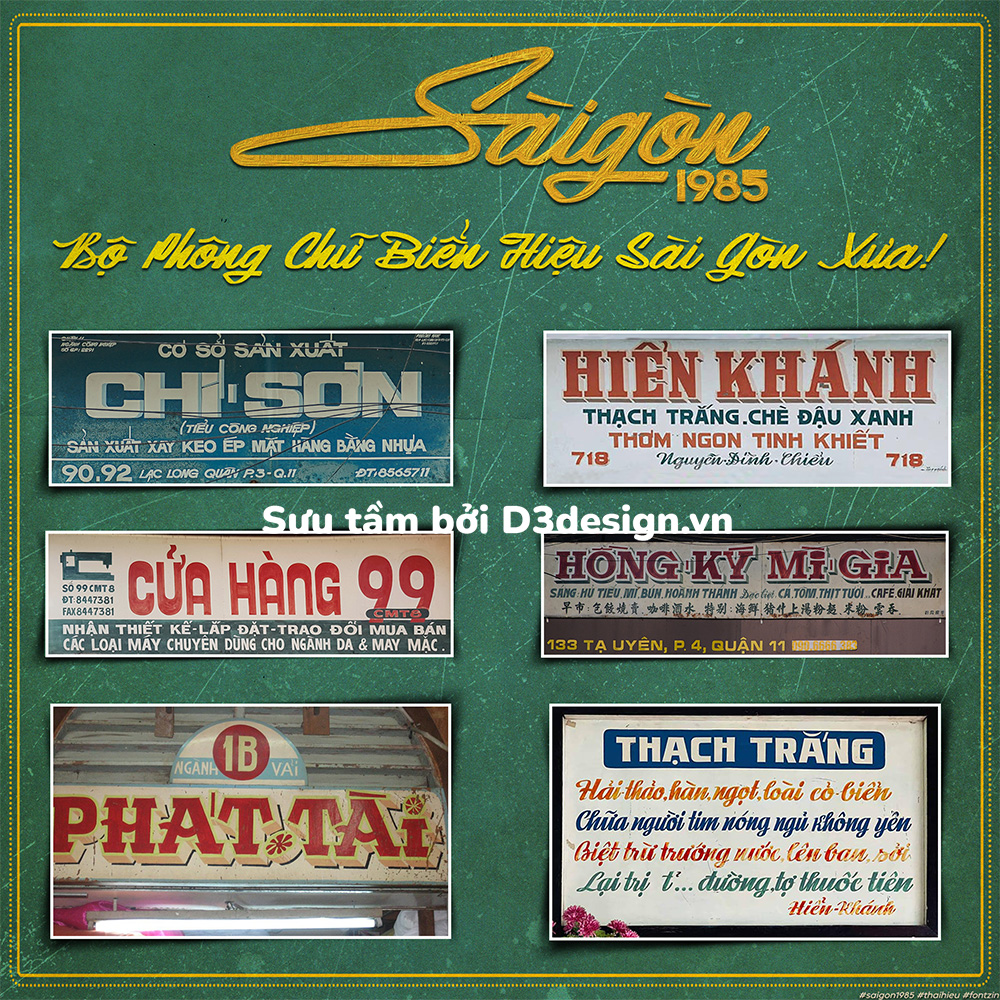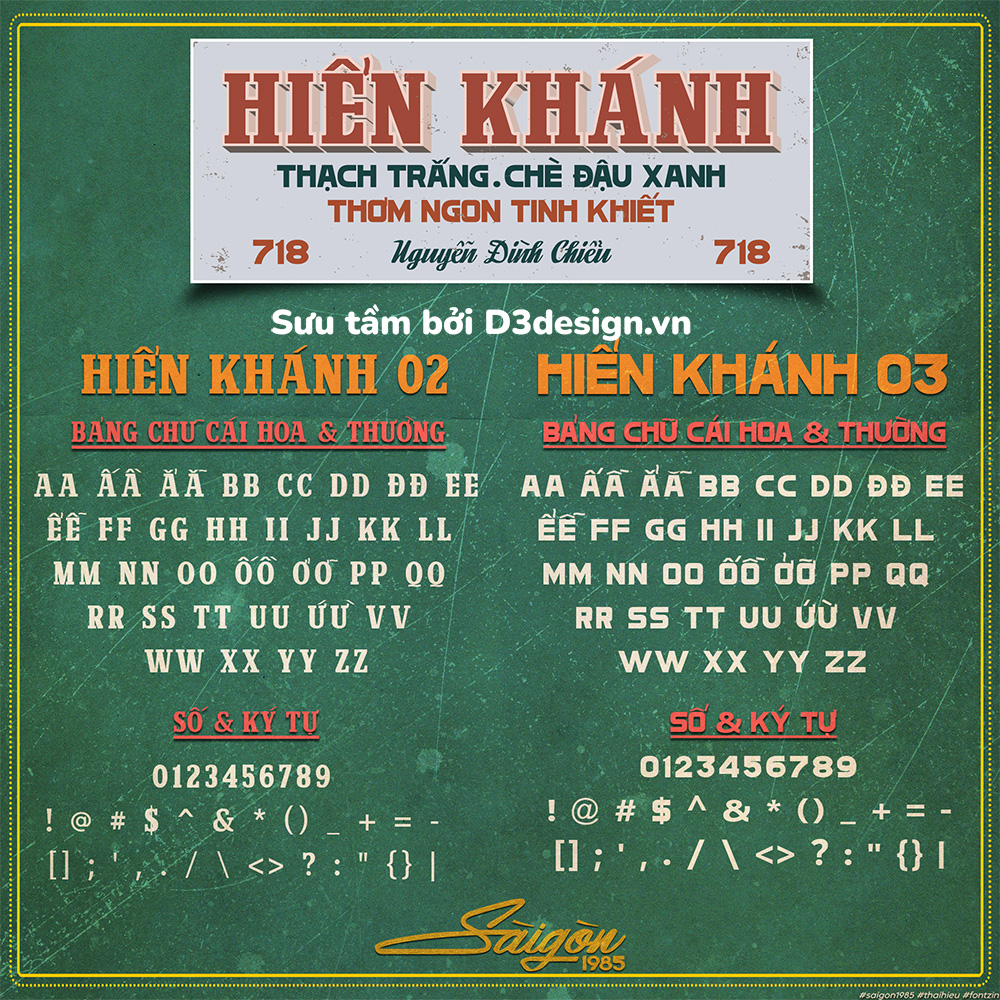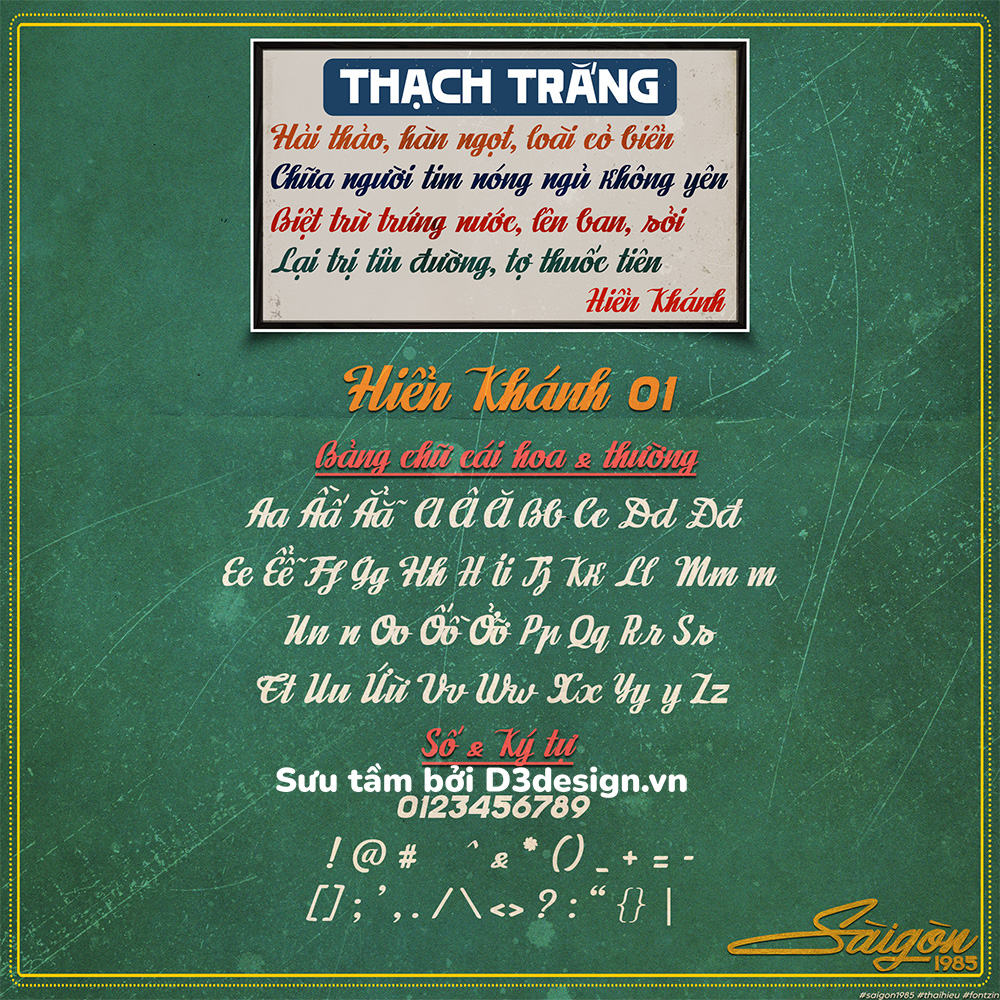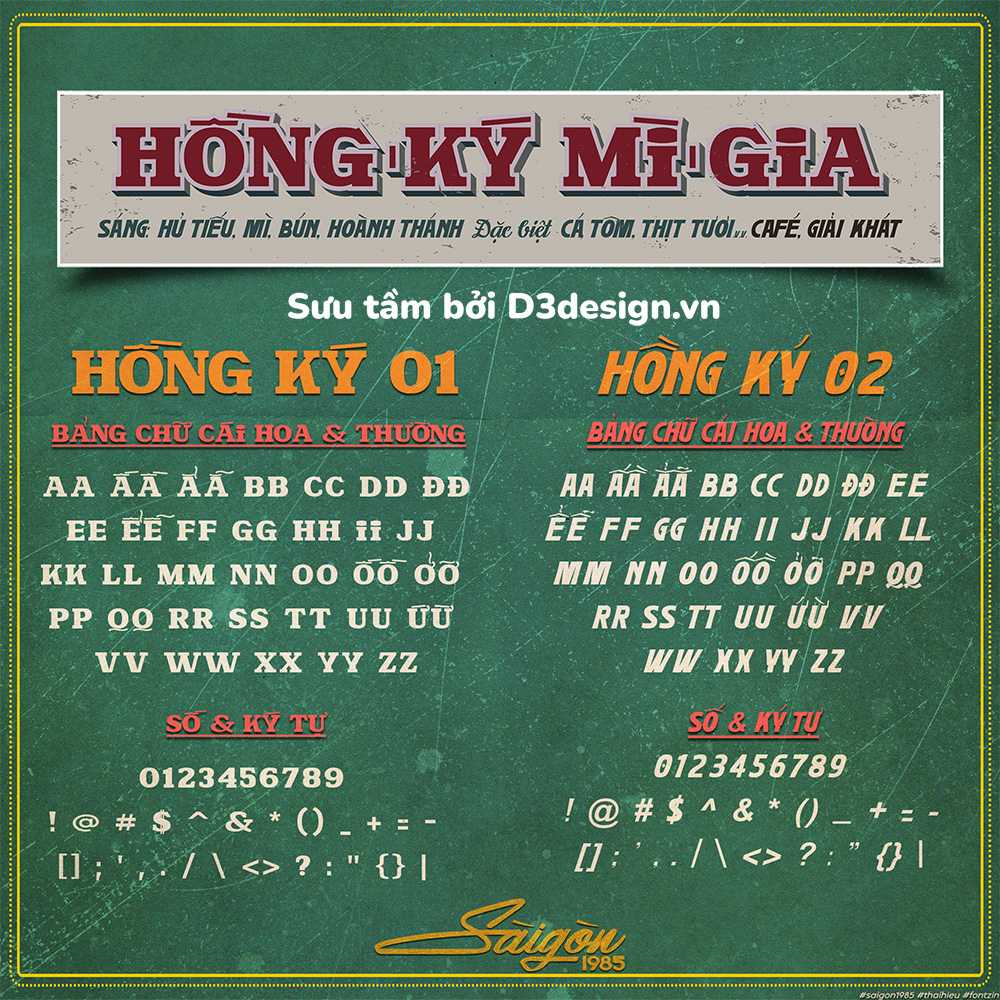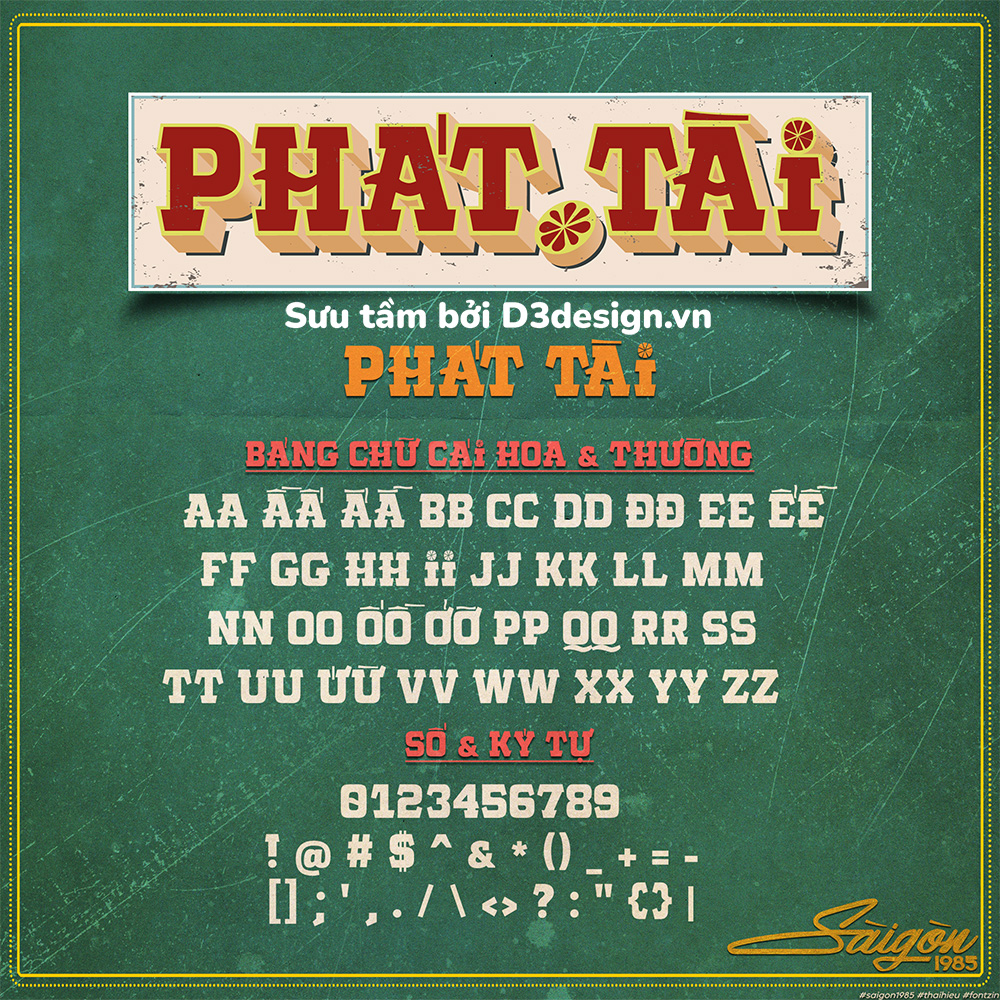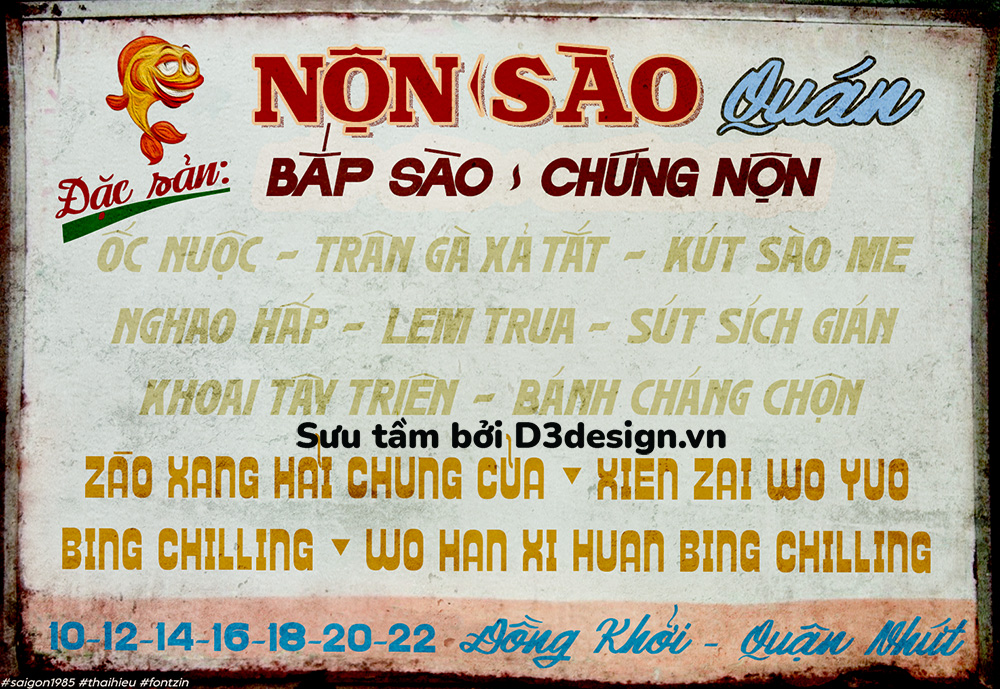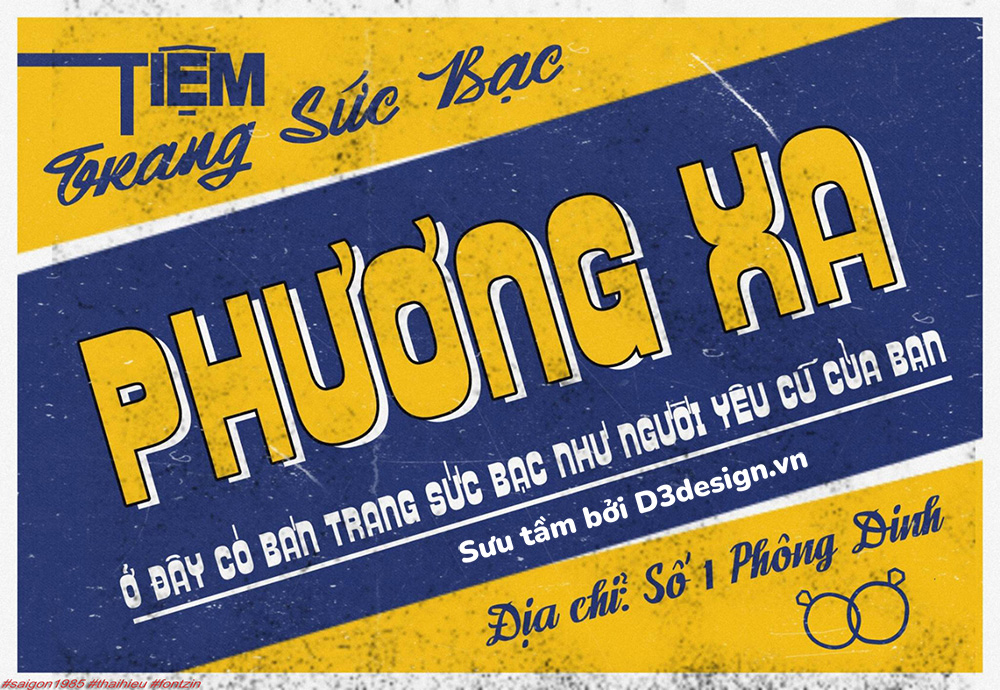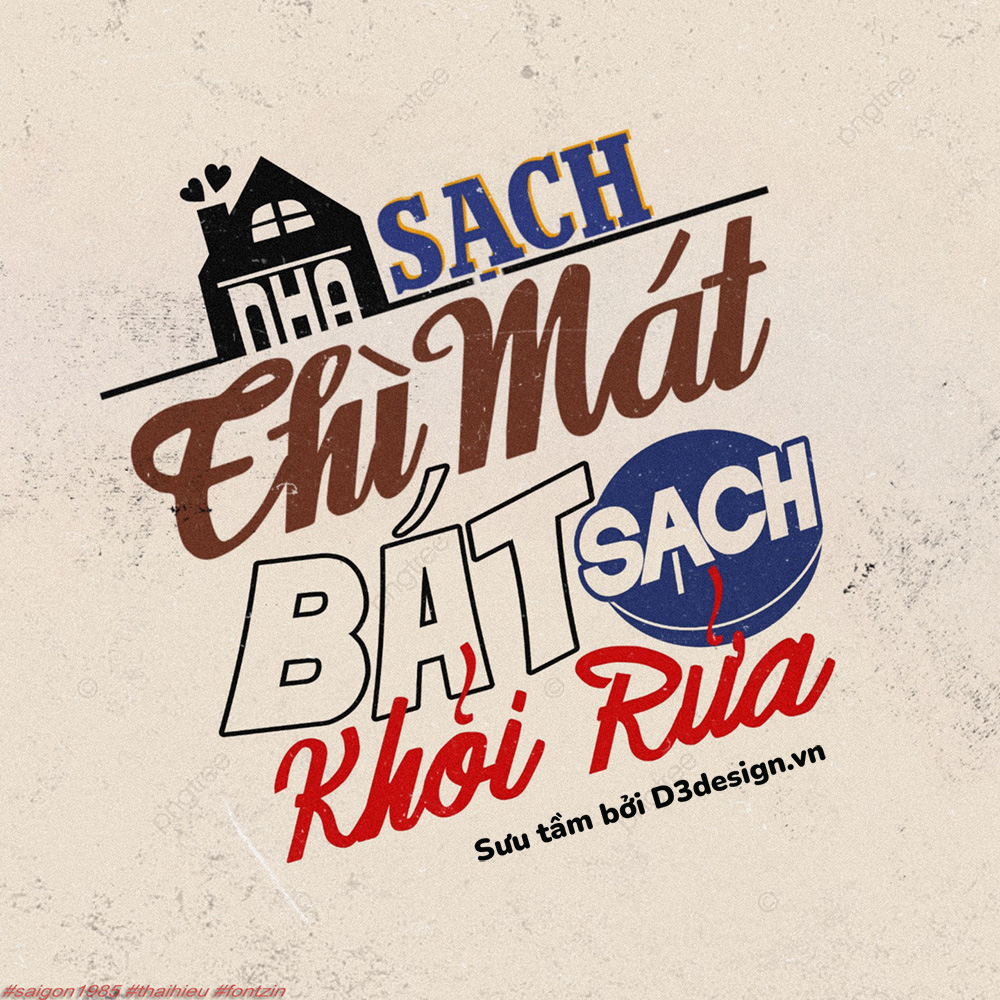
Font Xưa Việt Hóa "Sài Gòn 1985" Cực Đẹp, Nét Cổ Điển Việt
Dự án này bao gồm 10 Typeface, mỗi Typeface được remake dựa trên 1 số chữ cái trên các biển hiệu để làm thành 1 Font hoàn chỉnh bao gồm các chữ cái latin A-Z, số, ký tự cơ bản với kiểu dấu tiếng Việt nguyên mẫu, ngoài ra còn có 1 vài ký tự (chữ cái) thay thế khác. Tên Typeface mình đặt theo tên của biển hiệu.
Font được Kerning TV (khớp với chữ mẫu trên biển hiệu), hỗ trợ Opentype (Liga) trên máy tính & điện thoại. Một số Font có 2 kiểu dấu kết hợp và nhiều Style effect khác nhau.
"những thứ cổ, xưa, cũ luôn chứa đựng một cái gì đó rất giá trị, ngoại trừ người yêu cũ". Vì vậy, mình đã quyết định thực hiện dự án này. Mình rất đam mê Font chữ và cực kỳ ấn tượng với các nét chữ, dấu tiếng Việt, vị trí sắp xếp dấu... trên biển hiệu quảng cáo của những "đì-sai-nơ" thời xưa.